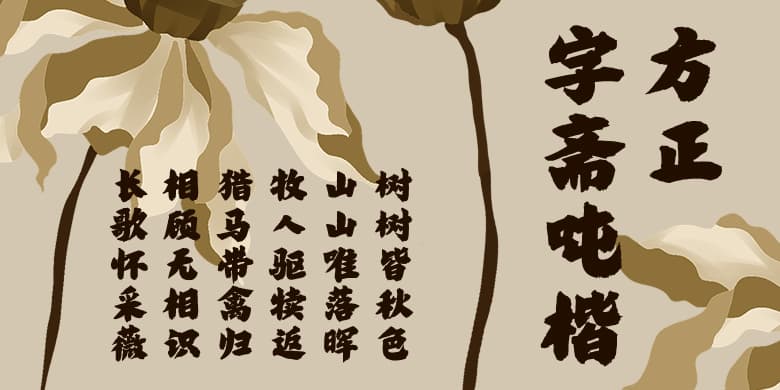
《方正字斋吨楷》是一款适合表达人文与力量相关属性的字体,其字体不但醒目,而且还有分量,可以给人新的视觉感知,唤起新的潮锐。这款字是立足于力量的创意书写,它与生俱来的视觉冲击力使其尤其适合作为标题字。
字体是有容颜的,有的长着一副大众脸,有的让人过目不忘,看似普通的字体,却暗藏着不为人知的能量。字体的容颜即字体的神态、神情、表情,外观相貌。能从表象、现象透出来的本质、实质、特质才是产品本身所想要诉求的。在字体中由形推神到质,通过设计是可以倒推出来。对字体进行察言观色,不失为一个好方法。